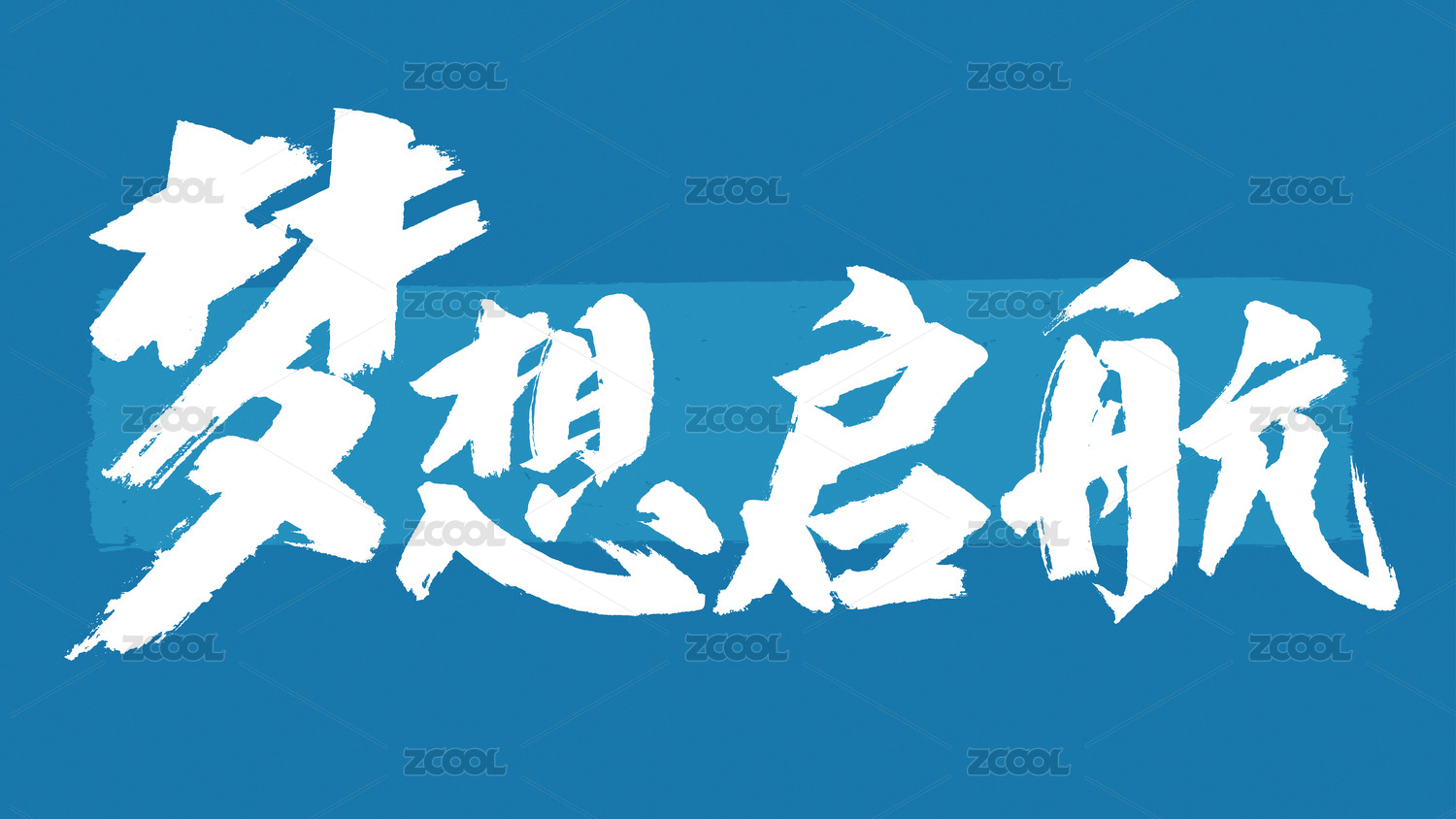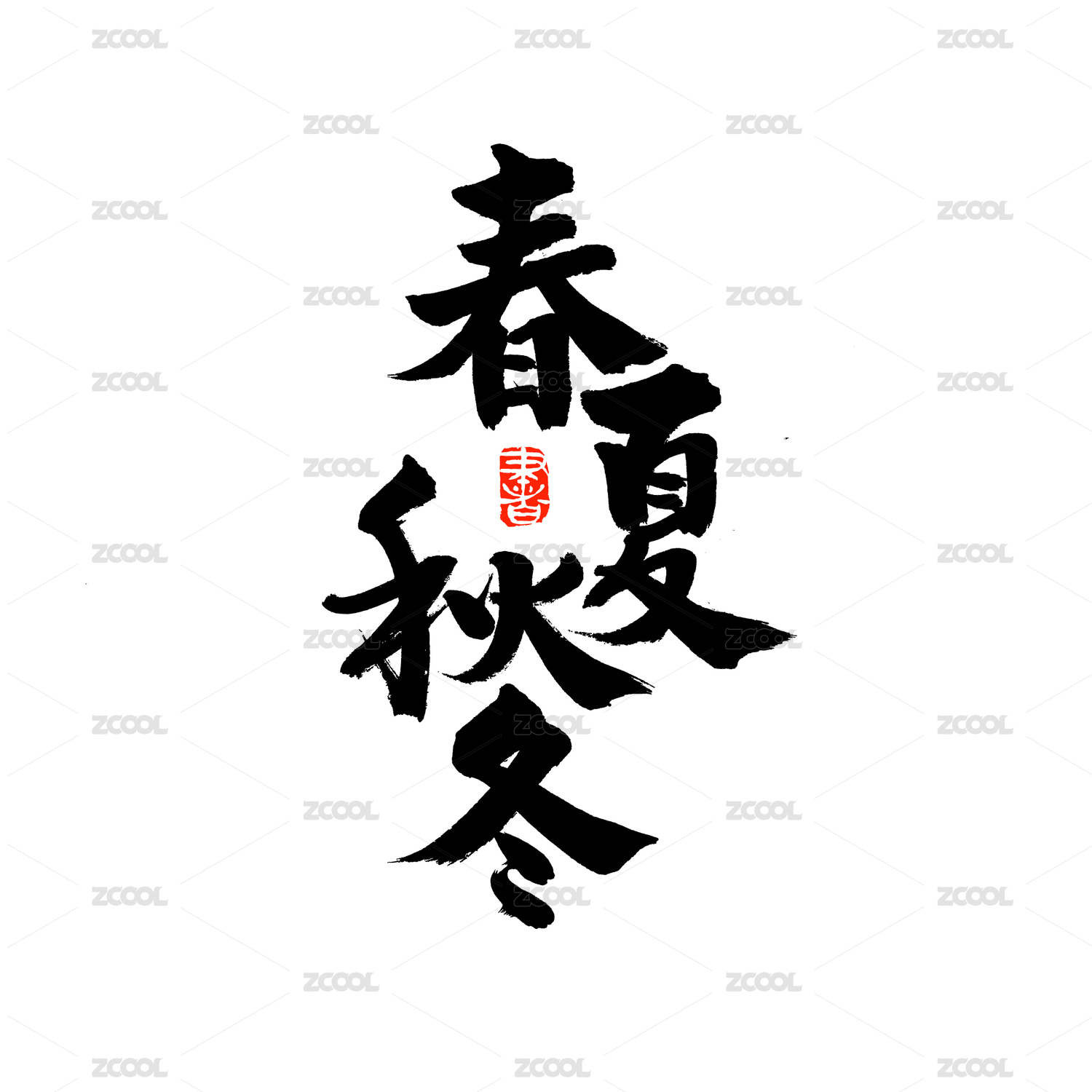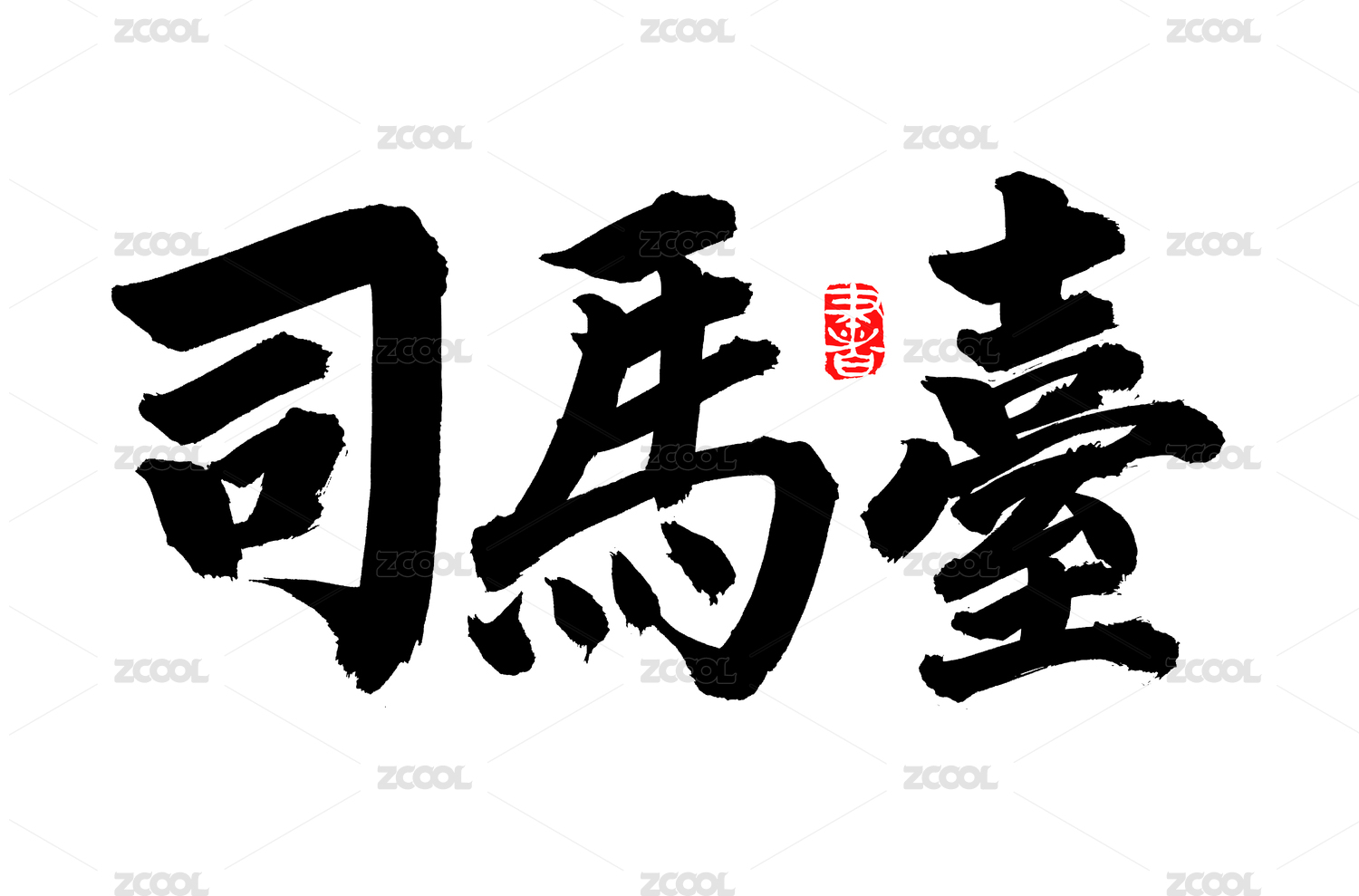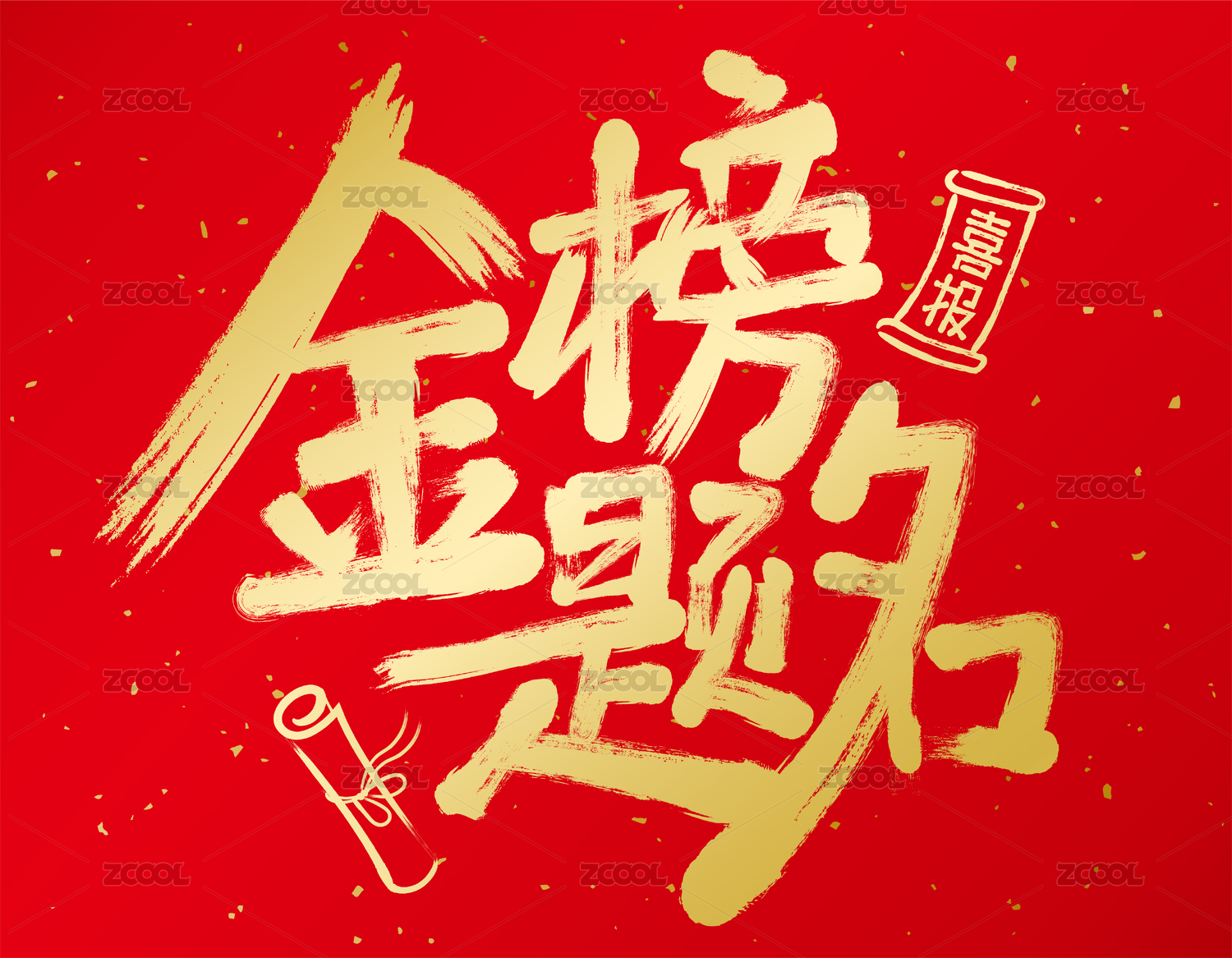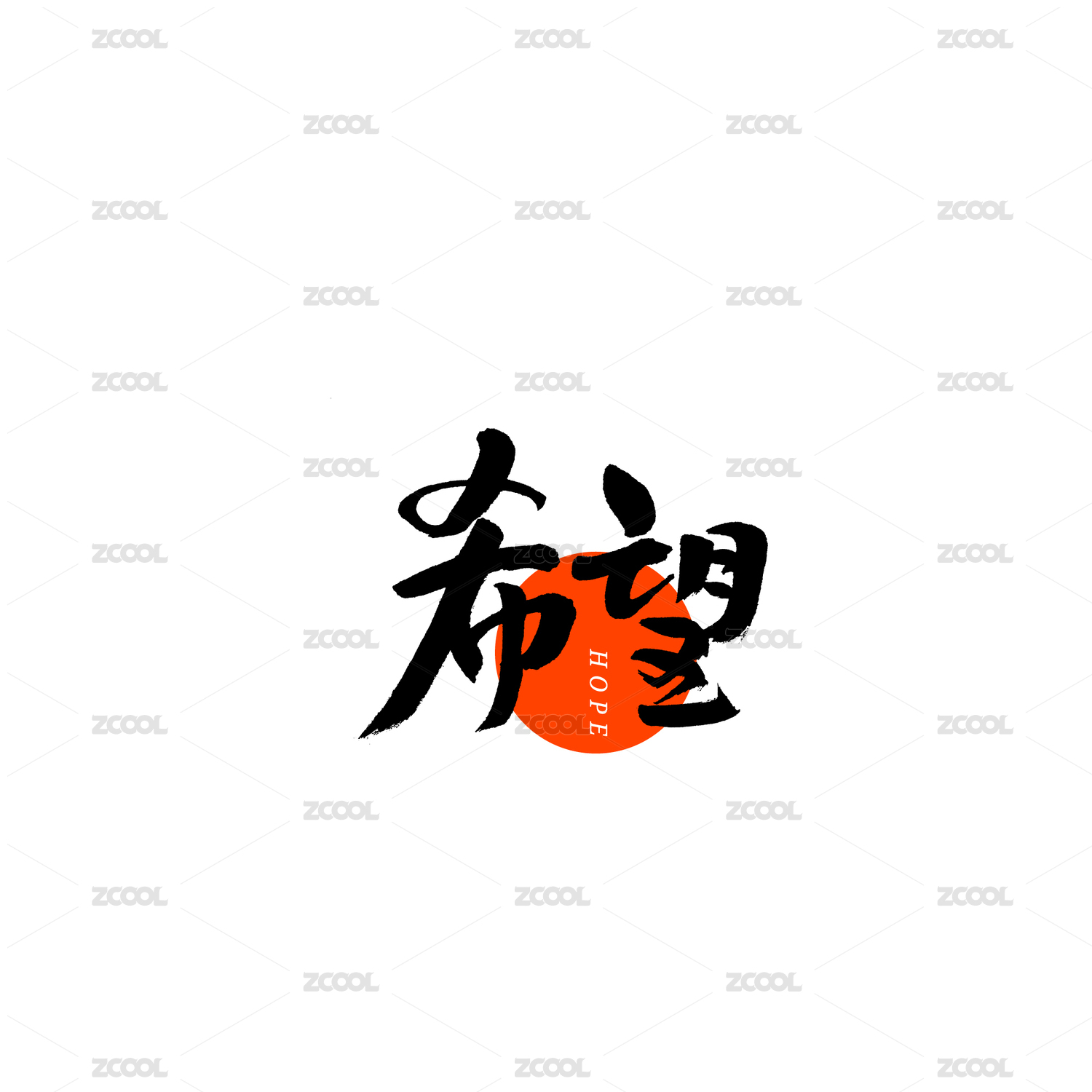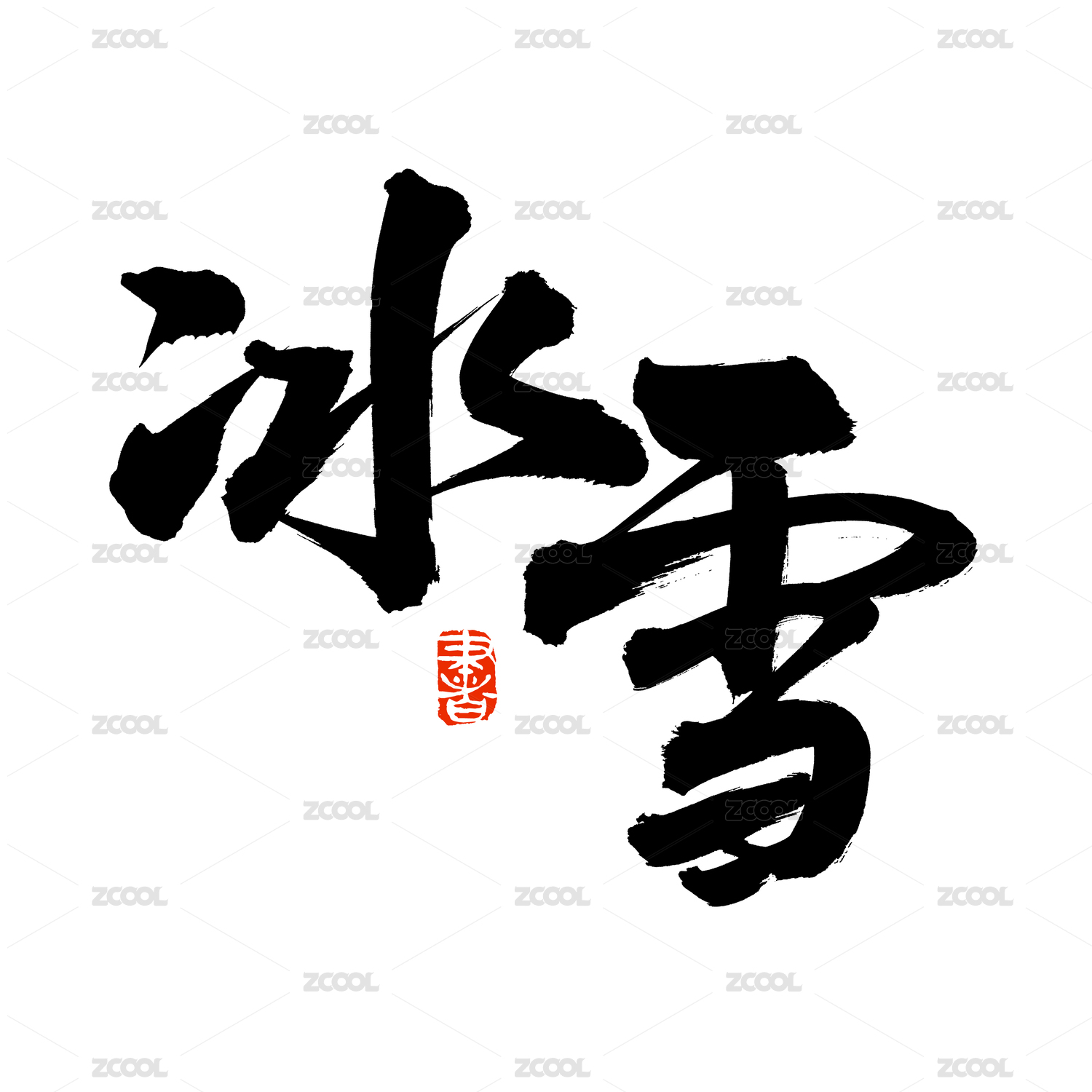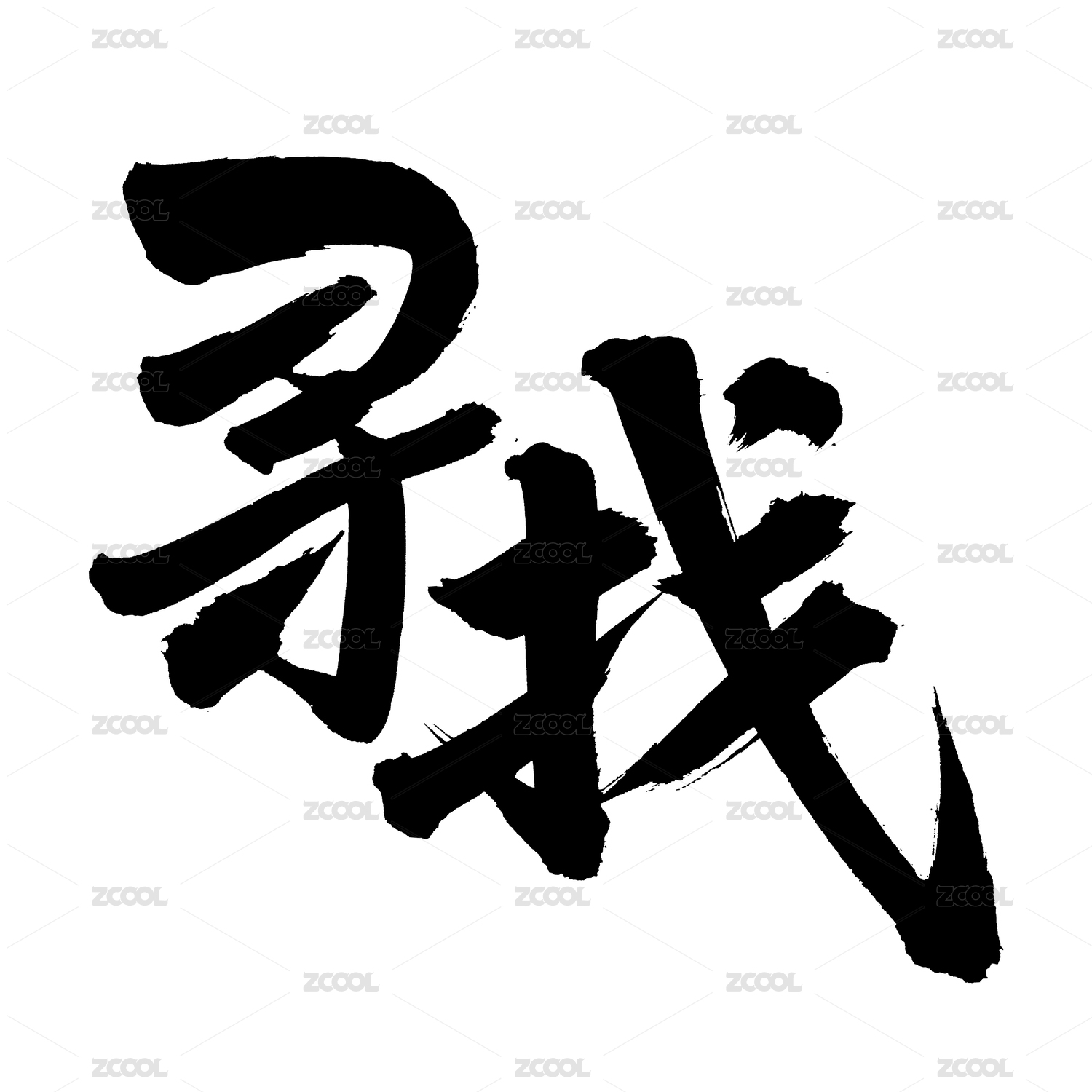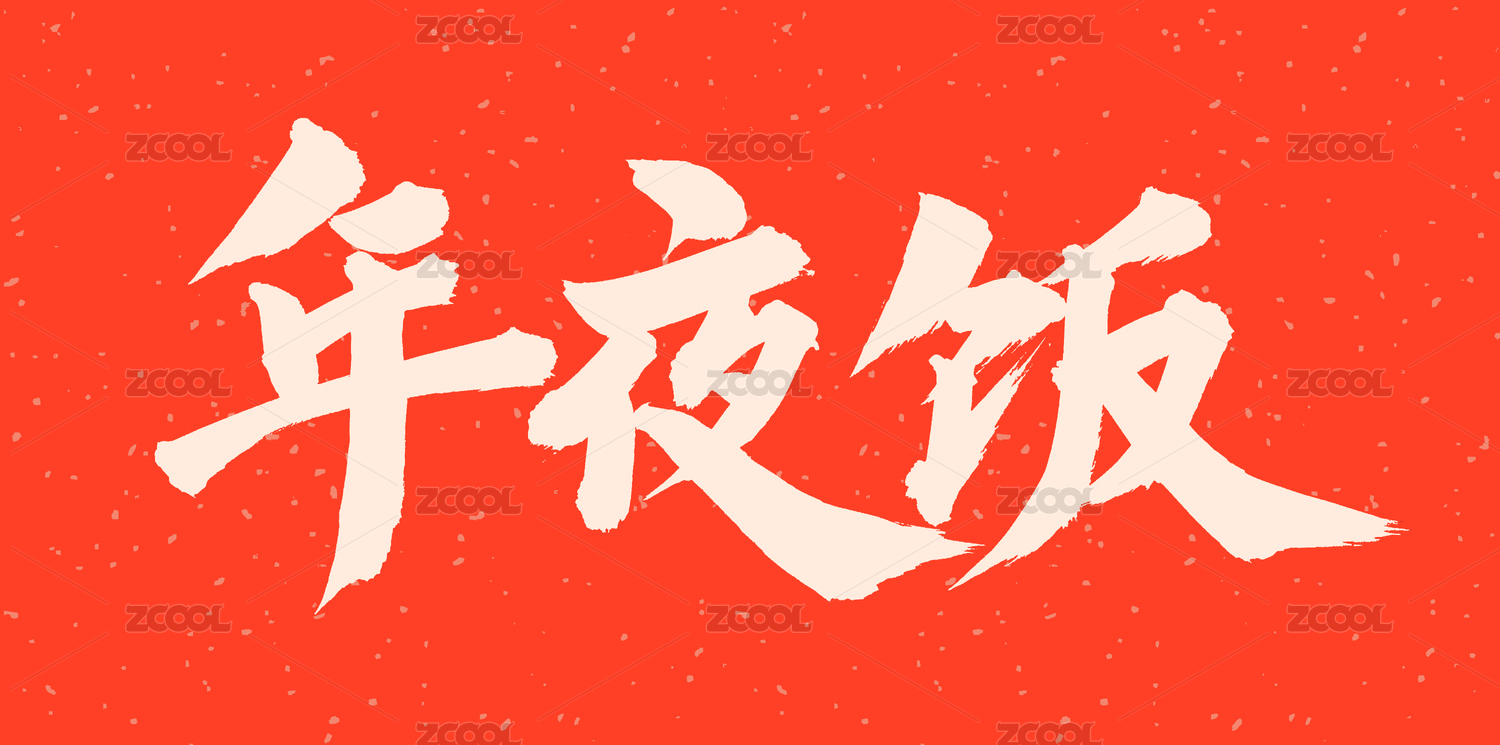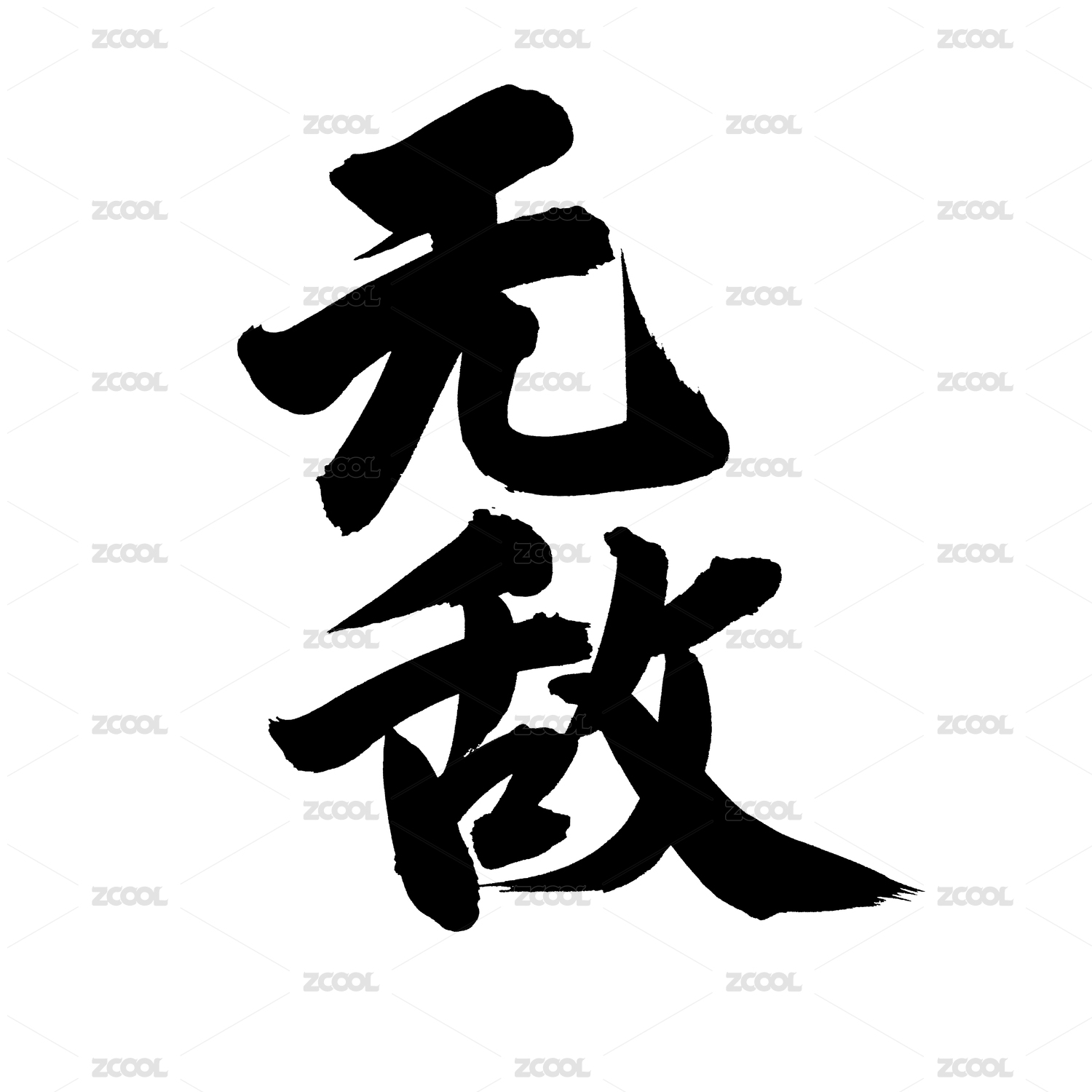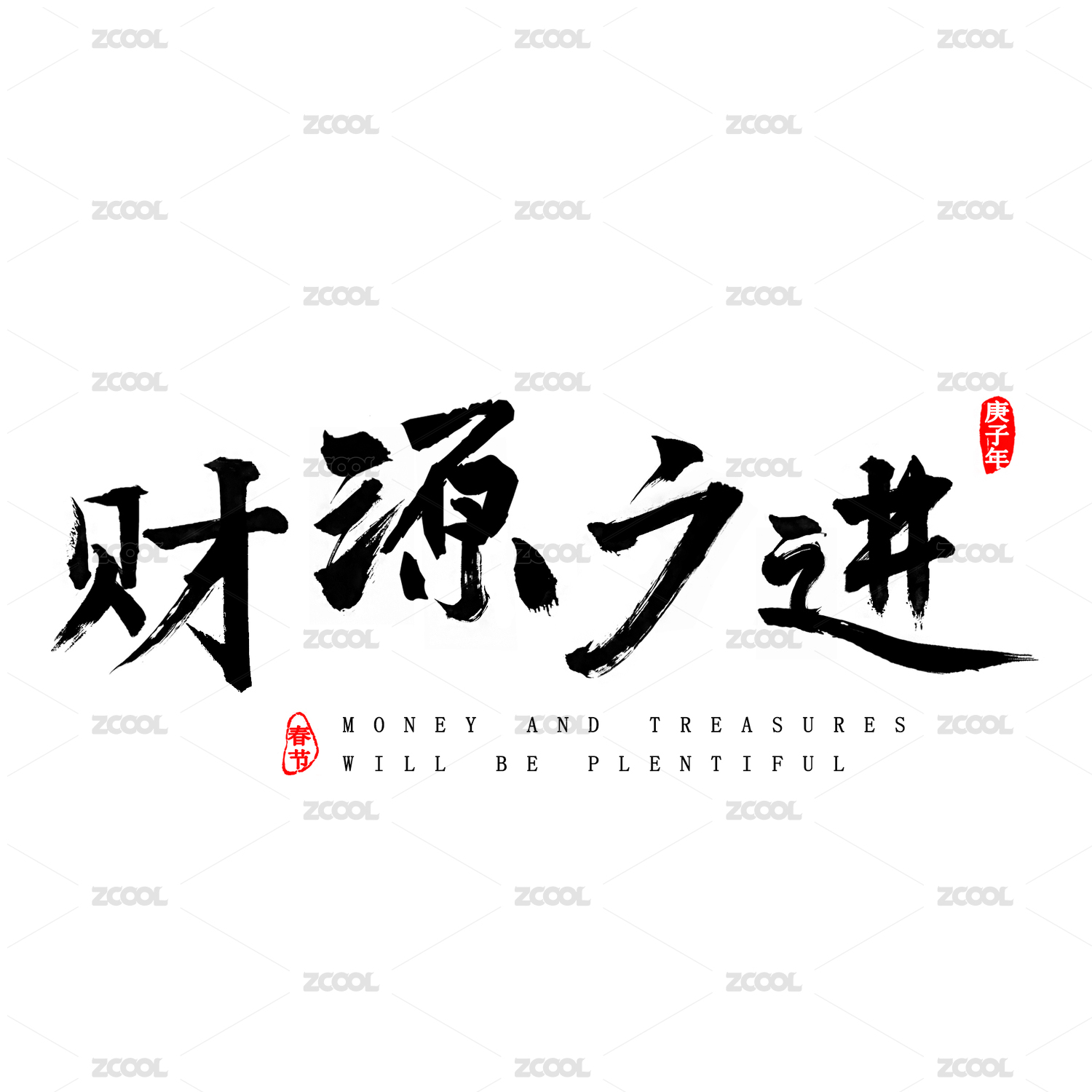
老樵书法
老樵,斋号: 顿渐草堂。山东乐陵人,现为中国东方文化研究会会员,山东省书协会员(会员号:00188),山东联合大学艺术顾问,中国女娲书画院副院长, 山东电视台《齐鲁风采》栏目特约艺术顾问。2019年CCTV3春晚特约书法嘉宾。乐陵市厌次书社副社长。中国书法家协会艺术考评等级:专业一级。
三十年孜孜以求,四体皆能,尤工章今草、汉隶、简帛书。章草、简帛、隶书为两汉、魏晋时期的主要书法形式,率真,随性,雍容古雅,富有庙堂之气。风格多样且法度完备,或雄强、或隽秀、或潇洒、或朴茂、或严谨,如群星灿烂,达到了书法史上的艺术巅峰。后人莫能与之比肩者。千百年来历经沧桑与磨砺而长盛不衰。在书法界,尤其到了清代后期和民国之初,是挖掘秦汉魏晋书风的又一个鼎盛时期,有了很大的发展和创新,让古老的书法艺术焕发出新的风采,有了新的高度。
书不入魏晋,徒成下品。老樵书法取法高古,大有雍容质朴的汉魏遗风。虽有流变而不失古雅醇厚的风貌。返虚入浑,积健为雄,多年苦行僧似的磨砺与探索,使得他在追古维新的道路上,有了自己的创作风貌,且游刃自如。是当今书坛真正用作品来说话的实力派书法家,也是近年来新崛起的一批颇具影响力的书家新秀之一。极具发展潜力和收藏前景。
作品见于国内多家艺术期刊和报纸,以及电视媒体、腾讯新闻、搜狐、人民网等各大网站。陆续出版了《邱国才书法揽萃》等个人书法集,以及《大象无形》、《汉字演变的几个分支》等多篇学术性论文。多次为灾区和贫病个人举行义卖义捐活动,以精彩的笔墨为社会奉献着自己的热情和大爱。
老樵先生为人恬淡随性,不善言谈,不傲不争,惟嗜书而如痴,无一日不自新。遐时,多喜与友人以饮茶、抚琴等聊作消遣。偶尔参加一些社会活动。他的书法价值,随着岁月的磨砺和艺术的精进,逐年递增,他超迈的艺术胸怀,精湛的艺术高度,淡泊的人生观念,推动着他的书法成就不断地向着艺术巅峰阔步迈进。